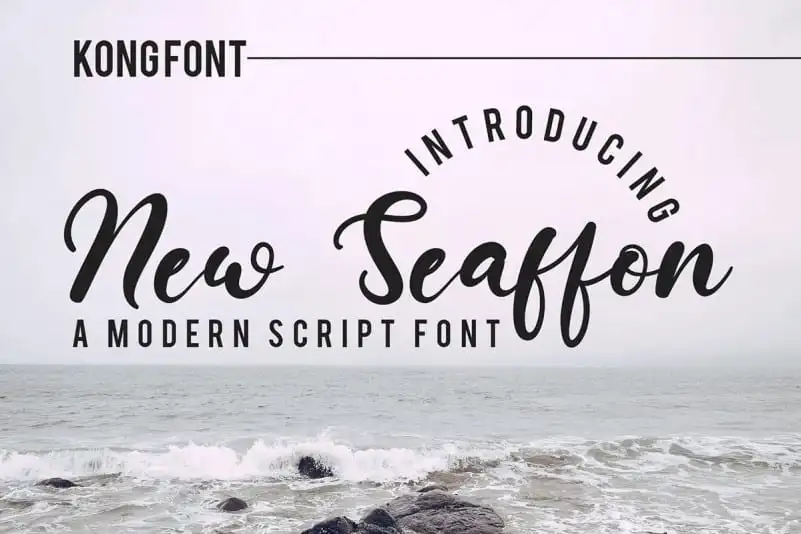
New Seaffon Script Font – Download Grátis
Nova Seaffon Script é uma fonte escrita a mão moderna produzida pela fontkong. Suavemente inserida na sua natureza, ela traz seu próprio estilo único para qualquer projeto de design. Ideal para criação, marca e identificação, convites, papelaria, designs de casamento, postagem nas redes sociais, anúncios, embalagens de produtos, designs dos produtos, etiquetas, fotografia e até mesmo watermark e eventos especiais. Este moderno fonte escrita a mão é perfeito para qualquer projeto visual que você esteja criando. Seja um designer de arte ou simplesmente alguém que gosta de adicionar algum charme às suas criações digitais, Nova Seaffon Script pode ser o seu próximo favorito.